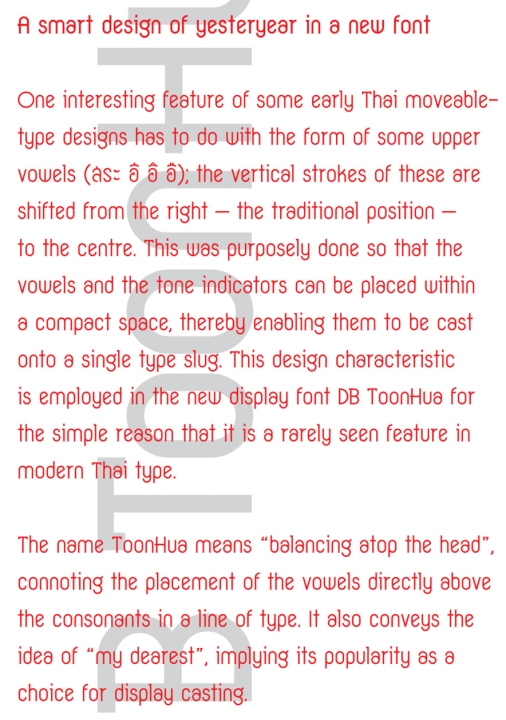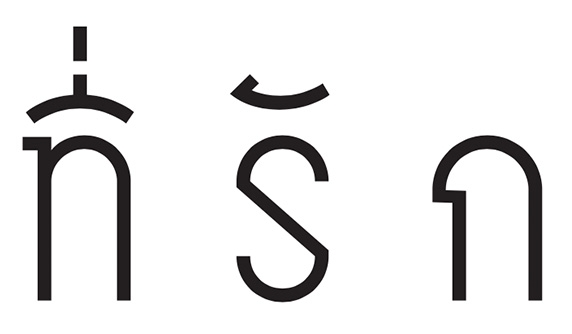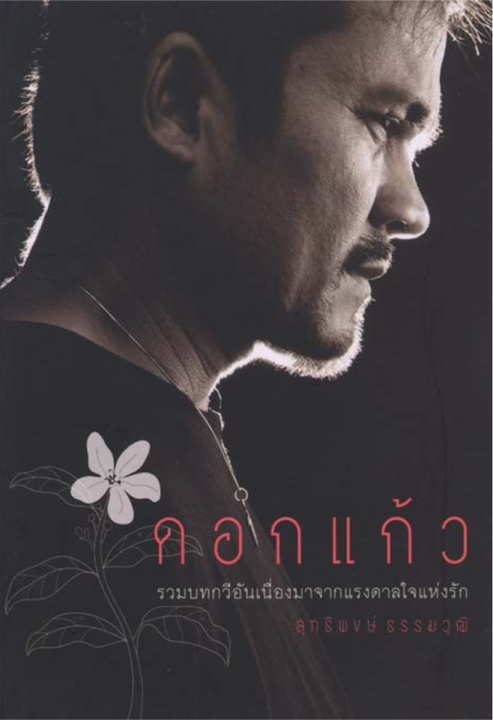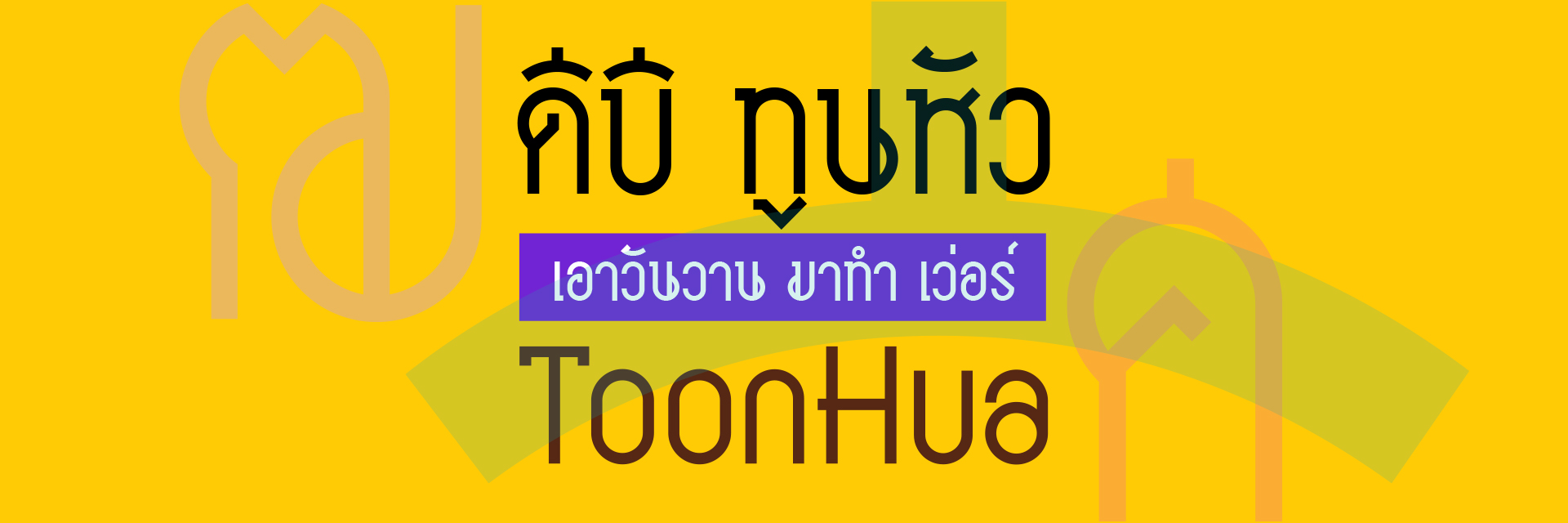
DB ToonHua
หากวิเคราะห์จากหลักฐานที่ปรากฏในงานสิ่งพิมพ์ไทยยุคต้นๆ จะพบรูปอักษร (glyph) มากมายของตัวเรียงพิมพ์ตะกั่วไทยที่แสดงถึงความชาญฉลาดในการออกแบบ เพื่อเอาชนะข้อจํากัดทางเทคโนโลยีการพิมพ์ในยุคนั้น ตัวอย่างเช่น การปรับเปลี่ยนรูปอักษรของสระบนไทยบางตัวคือ อี, อึ, อื ให้แตกต่างไปจากลายมือเขียนปรกติ กล่าวคือแทนที่เส้นขีดตั้งและวงกลมจะเป็นเส้นที่ลากต่อเนื่องจากรูปสระอิที่ปลายด้านขวา ผู้ออกแบบกลับเลื่อนหลบค่อนไปอยู่กลางแทน มีผลต่อเนื่องให้รูปวรรณยุกต์สูงถูกเลื่อนตามเข้าไปด้วย และหล่อทั้งรูปสระบนกับวรรณยุกต์ควบรวมเข้าเป็นตัวเรียงตะกั่วชิ้นเดียว
ถ้าจะให้ผมวิเคราะห์ว่าทําไมนักออกแบบชั้นครูยุคก่อน ถึงได้เลื่อนขีดของสระอีเข้ากลาง? เหตุผลน่าจะมีมากกว่าหนึ่ง. ประการแรกสุดน่าจะเป็นการช่วยให้มันดูห่างออกจากหาง ป ชัดเจนขึ้น
ตัวพิมพ์แบบบรัดเลย์เหลี่ยม" จากหนังสือบทละครเรื่อง "น้ําใจเด็ดเดี่ยว และปลอมกาย" หน้า 35 พิมพ์ในปี พ.ศ.2493 สังเกตที่วงไว้ แสดงรูปสระบนที่แตกต่างจากลายมือเขียนปรกติ
อาจมีข้อถกเถียงว่า น่าจะใช้สระอีที่มีขีดชิดด้านขวา (อย่างลายมือเขียน) ได้อยู่ เพียงแต่เลื่อนออกไปให้ห่างจากหางให้เพียงพอ คําตอบของผมคือ สระอีแบบนี้จะเกะกะกับรูปสระหรือวรรณยุกต์ของตัวพยัญชนะที่อยู่ด้านหน้า (อย่าลืมว่าเป็นตัวเรียงตะกั่วต้องมีช่องว่างทิ้งไว้ จะชิดชนกันแบบฟอนต์ยุคนี้ไม่ได้) ครั้นจะแก้โดยลดขนาดสระอีให้แคบลงก็คงไม่สวย. นี่จึงน่าจะเป็นเหตุผลประการที่สองของการเลื่อนขีดสระอี
ถ้าเราเรียงตัวพิมพ์ตะกั่วเป็นคํา “มิได้” เทียบกับ “มีได้” ด้วยระยะห่างของตัว ม กับ ไ ที่เท่ากัน จะเห็นว่าคํา “มิได้” ดูโปร่งกว่า “มีได้” นั่นเป็นเพราะมันแตกต่างกันที่ขีดสระ อี ด้านซ้ายสุด. ถ้าเราเลื่อนขีดสระอีเข้ากลางจะช่วยให้ “มีได้” ดูโปร่งเสมอกับ “มิได้” เป็นเหตุผลประการที่สามซึ่งเกี่ยวกับการจัดช่องไฟให้สมดุลย์ (คล้าย 2 เหตุผลที่ผ่านมา)
"ดอกแก้ว” รวมบทกวีของ สุทธิพงษ์ ธรรมวุฒิ ออกแบบปกโคย เกียรติภูมิ แก้วปลั่ง ด้วยฟอนต์ DB ToonHua
ประการที่สี่ ถ้าพิจารณารูปสระอี, อึ, อื จะพบว่าถ้าขีดและวงกลมอยู่ชิดติดปลายด้านซ้ายจะมีโอกาสเป็นจ้ำได้สูง เนื่องจากเป็นการพิมพ์ระบบเลตเตอร์เพรสบนกระดาษ ไม่เคลือบผิวเป็นส่วนใหญ่ หมึกอาจซึมจนดูไม่สวยงามและอ่านยาก. การออกแบบจึงควรลดจุดบรรจบรวมของเส้นเพื่อเลี่ยงความเข้มที่เกิดจากหมึกซึมเข้าหากัน นั่นคือต้องเลื่อนขีดของสระอีเข้ากลางสถานเดียว
ไม่ว่าจะเป็นเหตุผลข้อใด (หรือถูกหมดทุกข้อ) โดยสรุป คือเป็นไปเพื่อให้งานพิมพ์ดูโปร่งสบาย ชัดเจน อ่านง่าย เป็นหลักนั่นเอง ลักษณะเด่นของรูปสระอี, อึ, อื ที่ว่านี้ถูกถ่ายทอดต่อมาในฟอนต์ DB ToonHua ด้วยเหตุผลง่ายๆ ข้อเดียว คือ สร้างความแปลกใหม่ซึ่งไม่เคยพบเห็นในฟอนต์ตัวพาดหัวตัวไหนของไทยมาก่อน
ในการออกแบบชุดสระอิ, อี, อึ, อื ผมลดรูปสระอิเป็นรูป โค้งคว่ำ. จากนั้นก็ตั้งขีดและวงกลมตรงกึ่งกลางเป็นสระอี, อึ, อื. หน้าตาของสระตัวใหม่ 3 ตัวนี้เสมือนเป็น DNA ของ "ทูนหัว" มีผลต่อเนื่องไปถึงลักษณะสําคัญของแบบตัวพิมพ์ทั้งชุด ไม่ว่าจะเป็นตําแหน่งวรรณยุกต์ การันต์ชุดสูง, ระบบของหางอักษร, หัวอักษรที่อยู่กลางตัว, หรือหัวที่หันเข้าหาลําตัว ฯลฯ
"พิชาญอนุสรณ์" จากปกหนังสืออนุสรณ์ในงานพระราชทานเพลิงศพ นายพิชาญ บุลยง ในปี พ.ศ.2506. ให้สังเกตความแปลกแหวกแนวของขมวดม้วนตัว น และ ณ ในยุคนั้น
‘นักพนัน’ พิมพ์ครั้งที่ 3 พฤษภาคม 2541 ออกแบบปกโดย ทองธัช เทพารักษ์ ตัว น มีเส้นฐานแบน ส่วนขมวดม้วนโค้งเป็นส่วนผสมระหว่างความเป็นเหลี่ยมแบบ "พิชาญอนุสรณ์" กับความโค้งกลมแบบ น ของ "ทูนหัว" ให้ความรู้สึกขัดแย้งไม่แน่นอน เข้ากับชื่อหนังสือได้เป็นอย่างดี (ตัว น ของ DB ToonHua มีส่วนคล้ายกับตัว น ของ ”นักพนัน" โดยบังเอิญ แต่เกิดช้ากว่าเกือบ 10 ปี หรืออาจมากกว่านั้น)
ตัวอักษรประดิษฐ์ของไทยในยุคเก่าที่มีหาง ศ, ส, ฮ อยู่แนวกลาง (ดูโฆษณาย่งกี่เลียบเฮง) จึงถูกนํามาใช้กับ ฬ รวมถึง ฐ ที่ได้อิทธิพลมาจาก จ ของ DB Soda ซึ่งมีเส้นตั้งอยู่กลางตัว
รูปอักษร ค, ด ของตัวตะกั่ว ฝ.ศ. ถูกปัดฝุ่นมาใช้ได้ดี เพียงแต่เปลี่ยนคอและหัวเป็นเส้นตรงประกอบกัน. ตัว ค ถูกหักปลายขึ้นตรงให้สัมพันธ์กับสระอี. ตัว ย ซึ่งมีหัวโน้มเข้าหากลางตัว (เหมือน ค, ด) จึงง่ายต่อการเติมขีดหัวในแนวดิ่งและส่งอิทธิพลต่อไปถึงหัวของตัว อ, ฮ
ลักษณะขมวดม้วนที่ฐานของกลุ่ม น, ฉ, ณ ที่พบในตัวประดิษฐ์ทรงเหลี่ยมยุคเก่า (ดูคํา พิชาญอนุสรณ์) ซึ่งมีวิธีการเขียนพลิกแพลงนั้น มีส่วนเป็นแรงบันดาลใจให้ผมปรับมาใช้กับ "ทูนหัว" ได้ ทิศทางการเดินเส้นที่แบ่งเป็น 2 เส้นประกอบกันสามารถแทนด้วยเส้นดิ่งตวัดโค้งทวนเข็มนาฬิกาที่ฐานไปหยุดที่ตําแหน่งเลข 1 แล้วลากเส้นหลังดิ่งลงมาสัมผัสเลยไปจรดฐานโค้ง. ขมวดม้วนที่แหวกแนวเป็นพิเศษนี้ กลายเป็นจุดเด่นสําคัญของ "ทูนหัว" เพราะตัว ม และ น เป็นตัวสะกดที่มีใช้บ่อย อีกทั้งยังมีสมาชิกที่เป็นตัวคล้าย (มีขมวดม้วนที่ฐานเหมือนกัน) อีกเป็นจํานวนมาก
ตัวอักษรประดิษฐ์ "ย่งที่เลียบเฮง" (พ.ศ. 2483) สังเกตคําว่า ที่ มีขีด สระอี อยู่กลางมาก่อนปัจจุบันแบบตัวอักษรนี้ถูกอนุรักษ์เป็น ฟอนต์ DB Ploenjit
ลักษณะรวมๆ ของฟอนต์ทูนหัวที่ปรากฏในขั้นนี้ คือเส้นบนและเส้นล่างจะเป็นโค้งครึ่งวงกลมแทบทั้งหมดเชื่อมต่อกับเส้นในแนวตั้งเป็นส่วนใหญ่, ผมจึงเลือก ข, ง รูปตัว V มาใช้ รวมทั้งหาง ช, ซ แบบเฉียง และ ร, ธ ก็เลือกใช้เส้นทะแยงเช่นกันเพื่อ ‘แก้เลี่ยน’ นั่นเอง
อิทธิพลของสระอี ยังส่งผลมาถึงสระไอด้วย ในเมื่อเรายอมรับได้กับการเลื่อนขีดสระอีไปอยู่กลางมาเกินร้อยปีแล้ว ทําไมจะเลื่อนมุมหยักของ ‘ไม้มลาย’ มาอยู่บนเส้นตั้งให้ดูสมมาตรแบบตัว Y ไม่ได้!
จุดเด่นอีกประการหนึ่งของแบบตัวพิมพ์ชุดนี้ คือ ตัวเลขไทยทรงเรขาคณิตที่ผมบรรจงออกแบบเป็นพิเศษเพื่อให้ คนไทยที่รังเกียจเลขไทย (ว่าเชย) ลองเอาไปใช้ดู
เลขไทยของ DB ToonHua ใช้ร่วมกับ เลขอาราบิคของ DB Soda
ฟอนต์ชุดนี้เมื่อพิมพ์สระบนแล้วตามด้วยวรรณยุกต์จะดูซ้อนขึ้นไปในแนวดิ่งกึ่งกลางตัว เหมือนทูนของไว้สูงเหนือหัว ผมจึงตั้งชื่อว่า DB ToonHua ความหมายที่สอง ‘ทูนหัว’ เป็น คําจากยุคโบราณ (คล้ายที่มาของ DNA ฟอนต์) ใช้เรียกผู้เป็นสุดที่รัก
เป็นความรักอันลึกซึ้งซึ่งเกิดจากการเก็บเกี่ยวสิ่งประทับใจจากวันวานมาปรุงแต่งให้เป็นนิรันดร์
แม้จะมี "เว่อร์" บ้างก็ตาม เพราะความรัก!